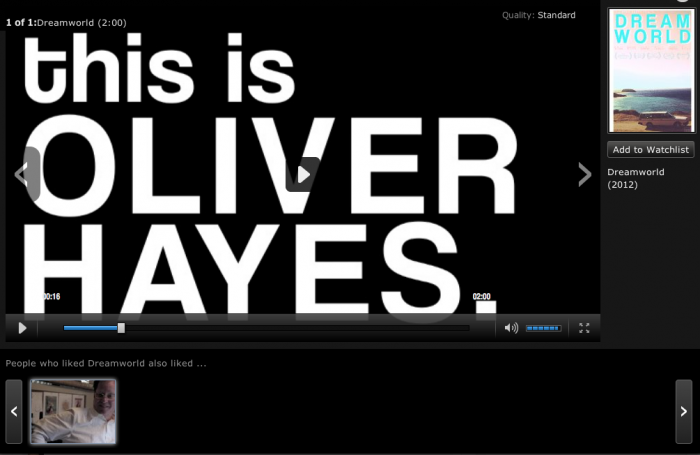
Suche Schrift aus dem Film "Dreamworld"
ich bin auf der Suche nach dem Font aus dem Trailer zu "Dreamworld".
Sehr speziell ist das "t".
Das ist auch die Coolvetica (das "R" ist sehr verräterisch)  :nicken:
na ja, grade das „R“ finde ich nicht so unterschiedlich. der querbalken im „t“ ist in der coolvetica allerdings deutlich leichter und somit dem screenshot ähnlicher. schwalbenkönig: recht hast!  :nicken:
stimmt, die Chalet hat das R ja ebenfalls so. War mir nicht präsent :-)